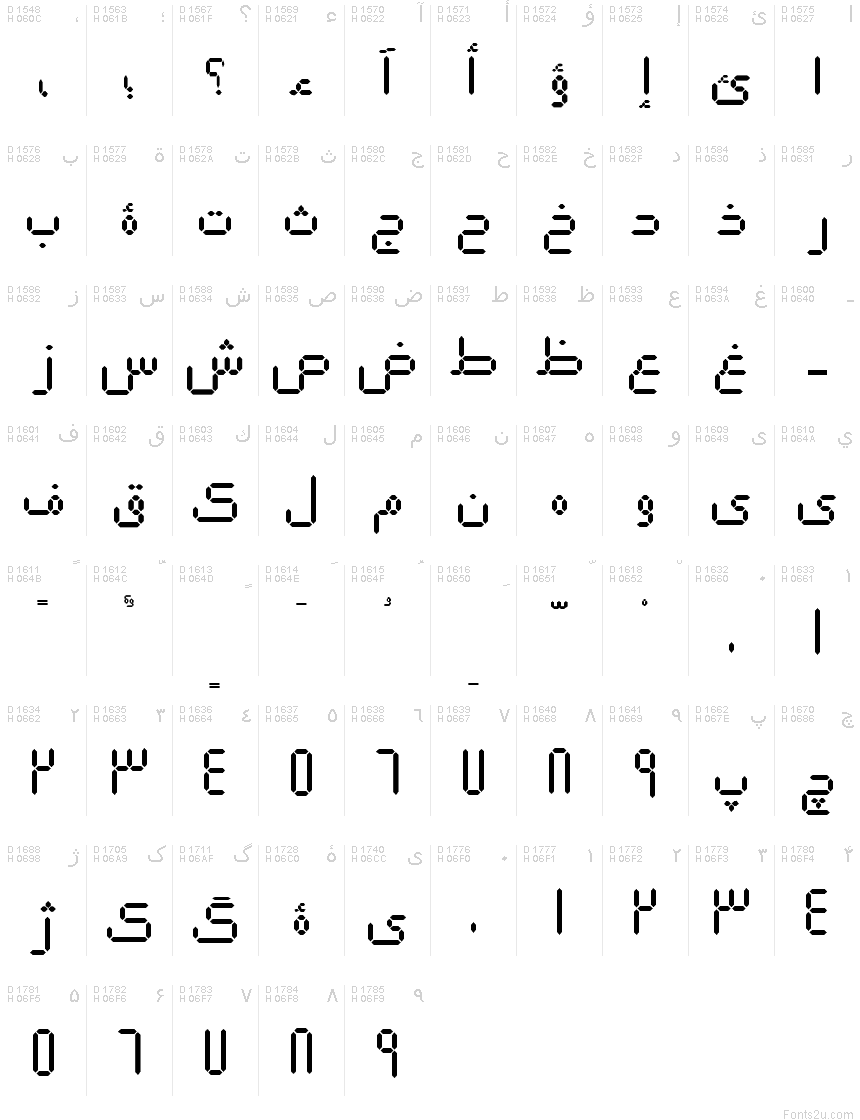
B Elm di Borna Rayaneh è un font display digitale gratuito di ispirazione araba, definito da tratti segmentati che scompongono ogni lettera in pezzi modulari e affilati. I tagli ripetuti e le giunzioni squadrate conferiscono ai caratteri un ritmo codificato, quasi simile a un segnale, che ricorda più un display personalizzato che una tipografia standard.
Questa frammentazione strutturata si presta al branding tecnologico, ai poster sperimentali, alla grafica ispirata all'interfaccia utente (UI), ai visual musicali e agli overlay per il gaming, dove un tono meccanico contribuisce a definire l'atmosfera. B Elm è perfetto per titoli brevi, schermate iniziali o concept di logo, specialmente quando si cerca un font gratuito dal tocco digitale distintivo, che faccia apparire il testo come costruito anziché scritto.